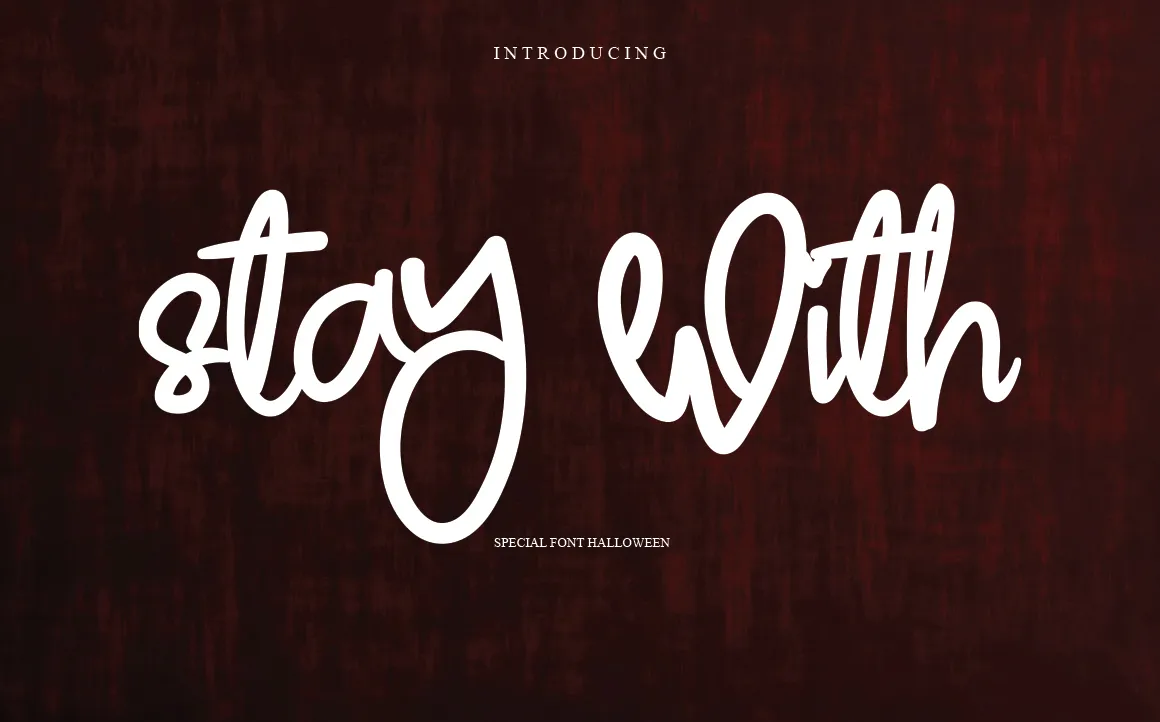
Stay With Font – Fonte Grátis
Stay With Font
A fonte ‘Stay With Font’ do designer levincreative é uma opção única, divertida e amigável para qualquer projeto criativo. Seja você queira criar conteúdo para Instagram ou um design de calligrafia DIY, esta font pode transformar a mais simples ideia em arte verdadeira. Com seu estilo handwritten, ‘Stay With Font’ oferece flexibilidade para diferentes ambientes e tamanhos de texto, tornando-a uma escolha perfeita para quem busca personalidade em suas produções digitais. Seja você designer gráfico ou artesão digital, esta font é um excelente complemento para o seu trabalho.